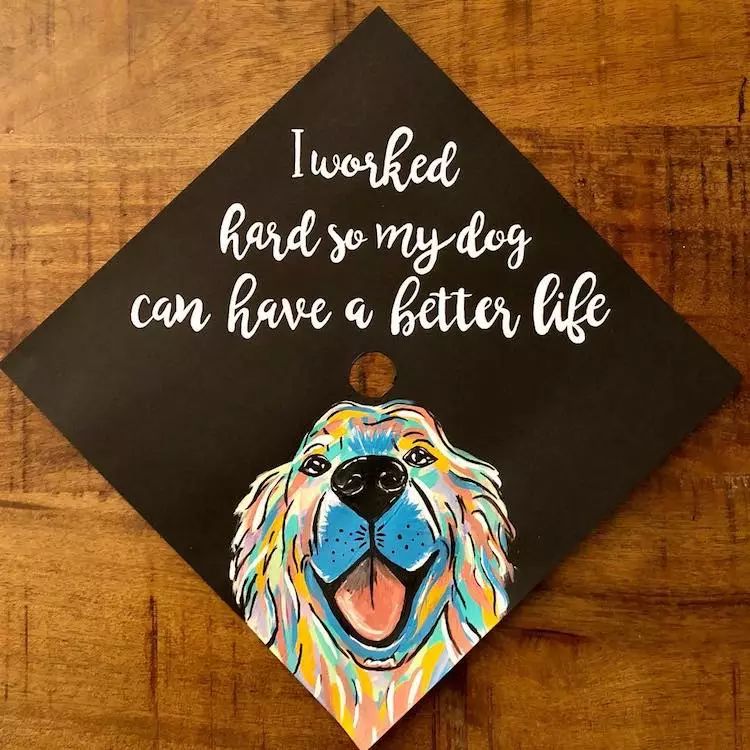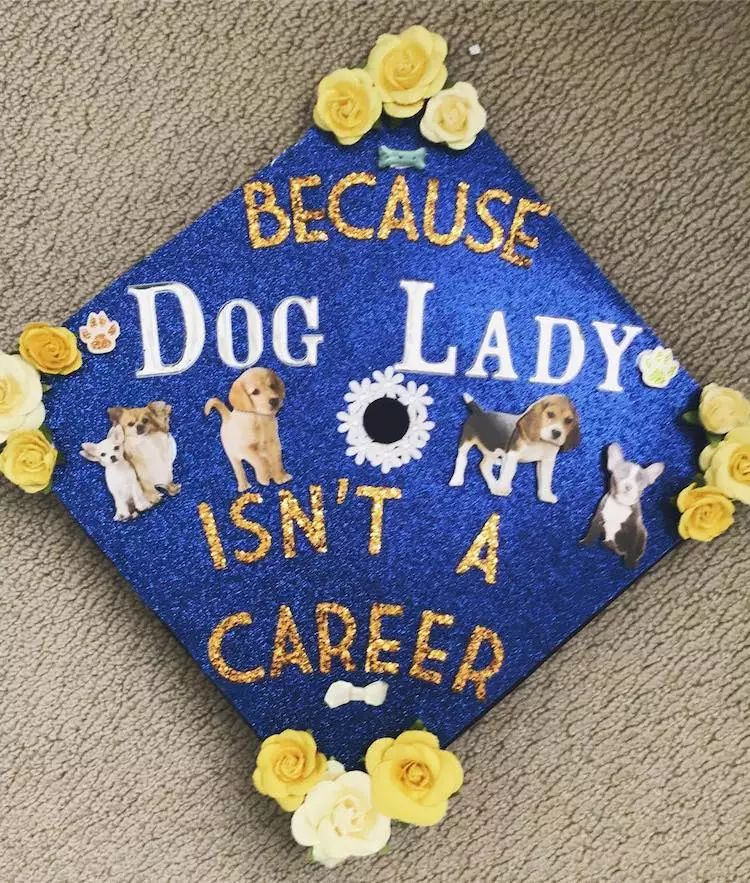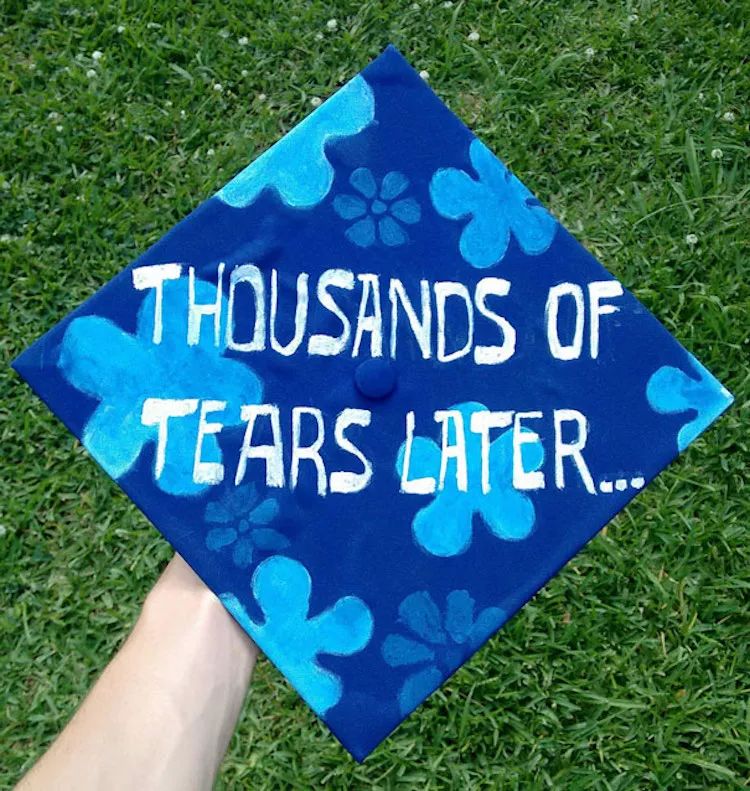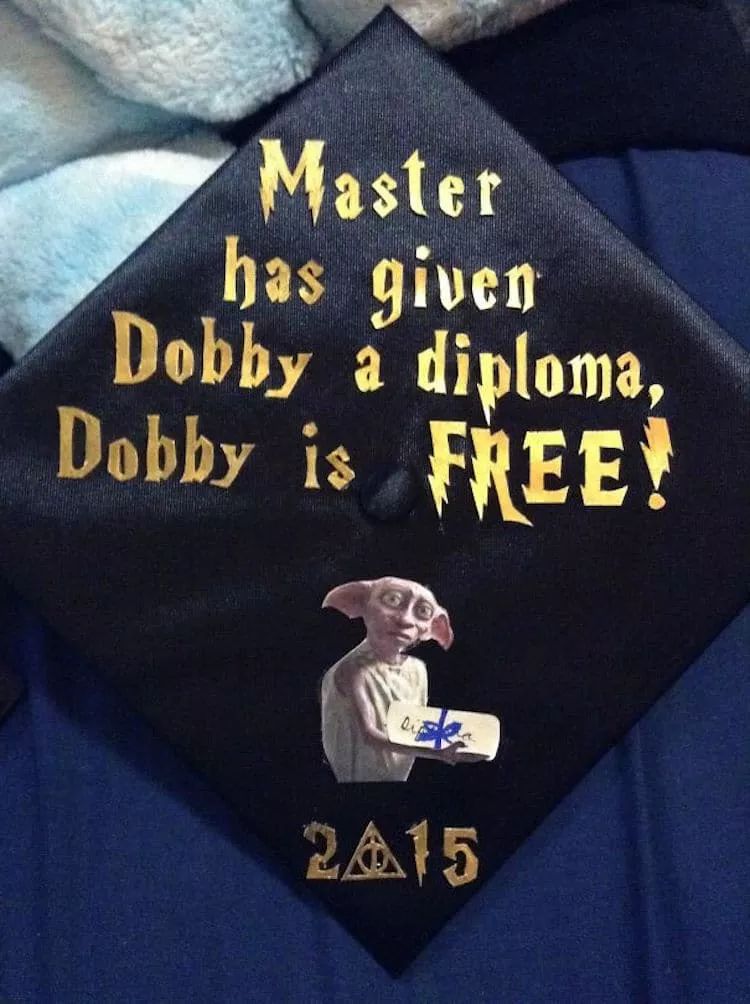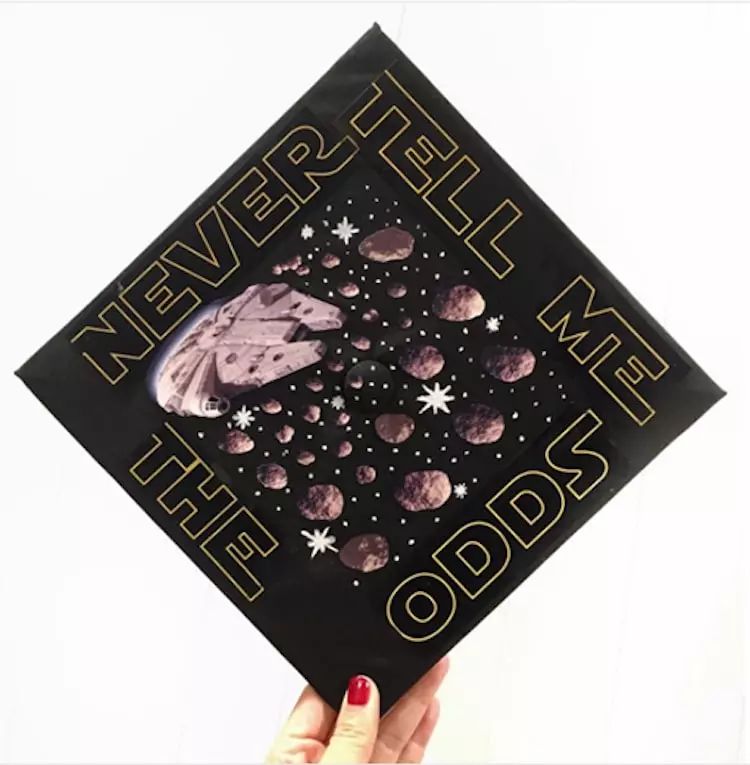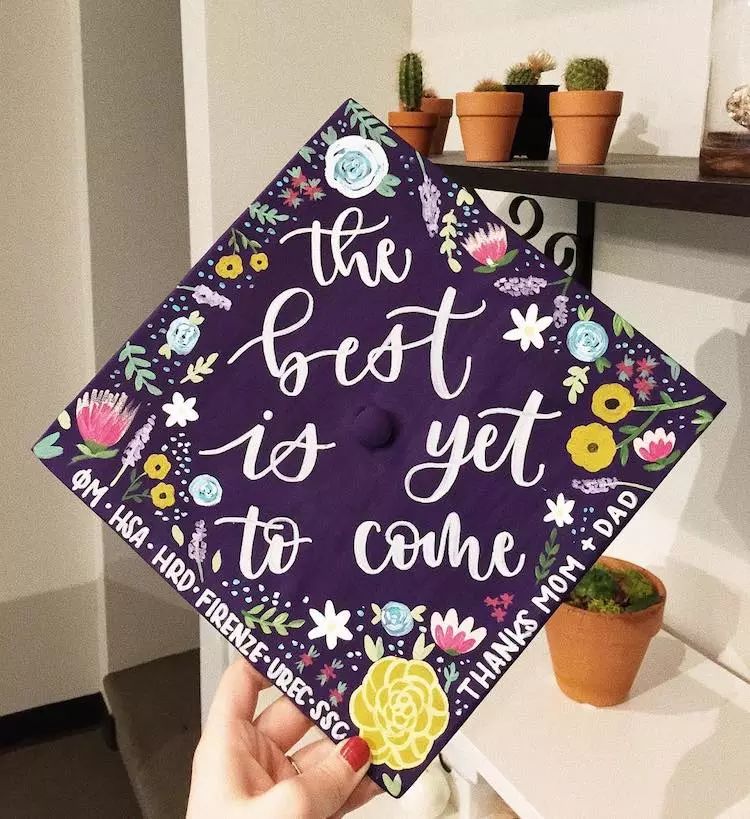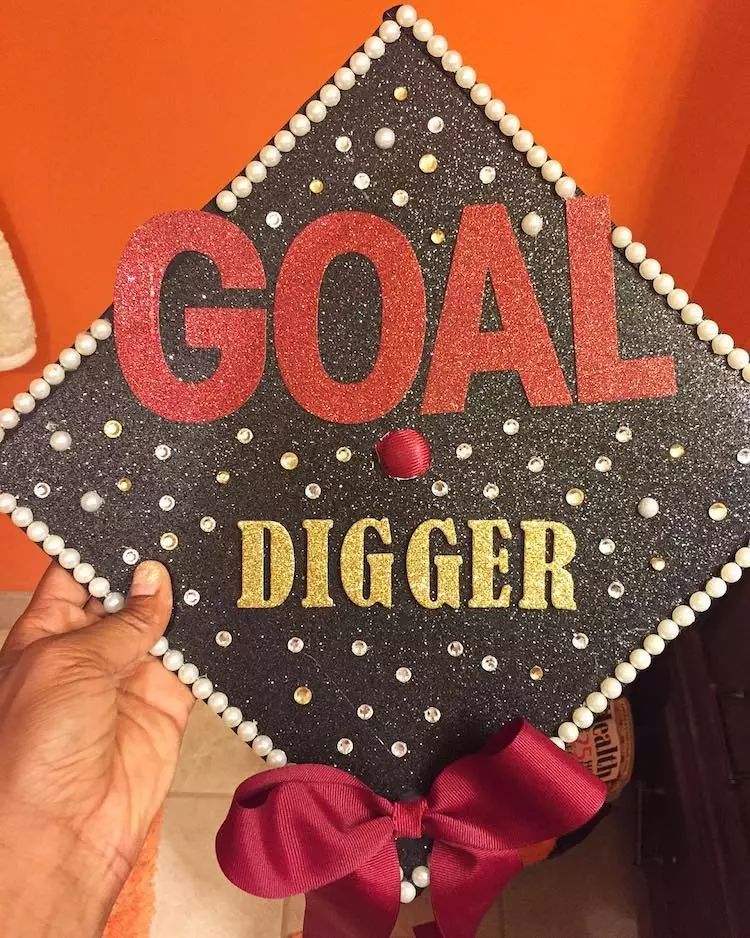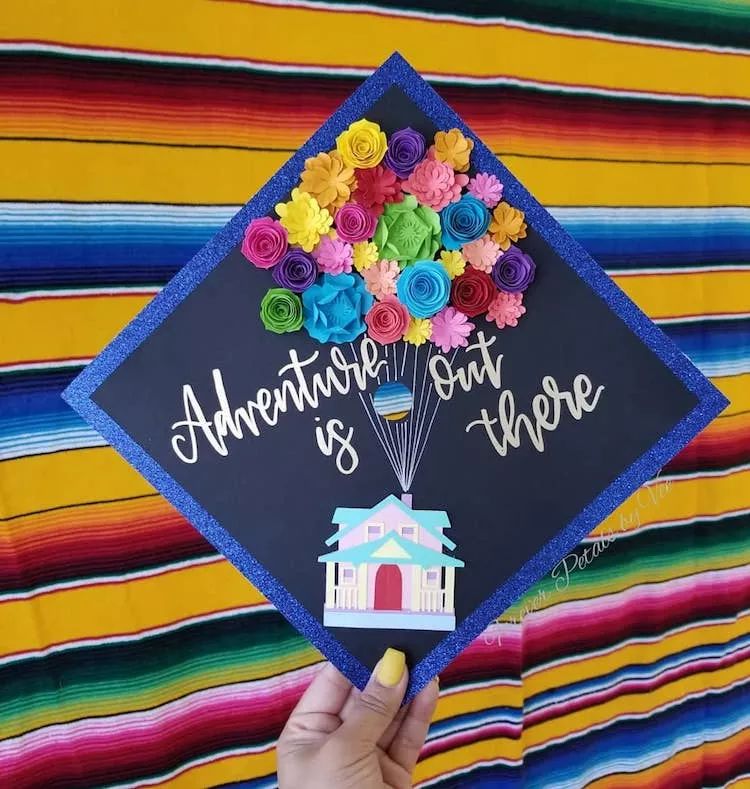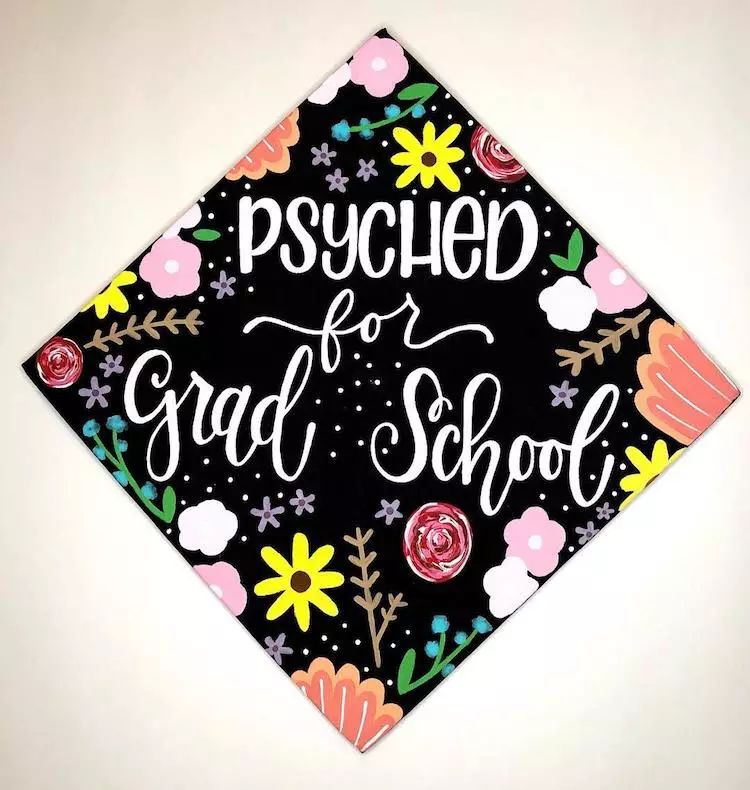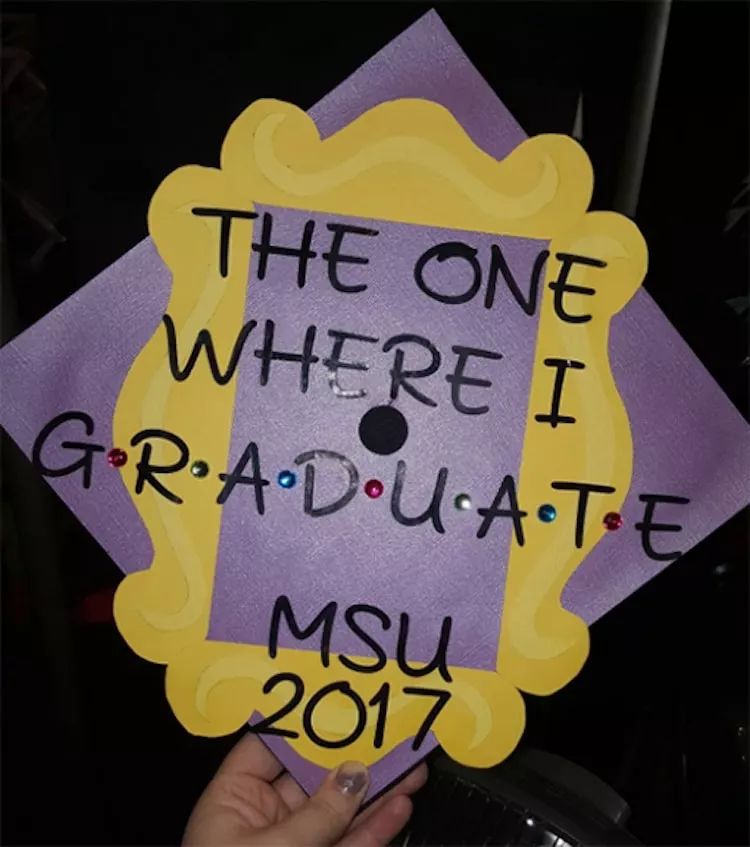
34款画风清奇的学士帽,看完我爱上了字体
转眼之间,已经是五月末了,每个学校的学长学姐们又要面临毕业了,又是一个平淡却又激情,朴素却又浪漫的毕业时节了。
就我个人而言,似乎每一次毕业都是那么的平淡,甚至没有什么让人感动的回忆——也不知道是我天性凉薄,还是校园生活太过乏味。
但真要说,其实「毕业」还是相当值得纪念的一件事,也是一个非常好的总结人生的节点。而最适合用来作为记录的载体之一,就是戴在你头上的学士帽。
我特意搜集了34个国外学生曾经「设计」的学士帽,并将他们分类展示给大家。也许他们的感叹和吐槽,能给你的毕业经历增添些灵感和趣味。
1.终于解脱的吐槽
虽然说校园里有着青春的各种美妙回忆,但是每个人总是会有些想要吐槽的事情,那么写在帽子上给所有人看就是一个很好的选择——让全世界人都知道你有多努力!
比如说这位emsgemscreations就表示:要不是为了我家狗子,我哪能成功毕业呢?!!!
当然也有比较感伤的,breckenh满是失望的表示:照顾自家狗狗确实不能写进简历里……
除了这些铲屎官,也有真正对于校园生活的吐槽。比如这位island-photo明显就是熬了夜的,估计通宵好久了吧。
也有对于一些社会问题的反应,eyeroll-qween也许就是熟练地运用了反讽的手法:没错,老娘就是来抢你们工作的移民,来打我啊!
而lizziehjelle的话,更像是一个宣言:然而,她坚持了下来!这孩子一定非常的努力吧!
2.满怀诚意的感谢
有吐槽,自然就有感谢。每一段人生,总有一些话要对一些人说。比如我们的家人:
来自erbanqueen
ampupino表达了对于父母的感谢也就算了,那个coffee明显把画风搞跑偏了呀!
事实上,果然有一大票跑偏了的感谢出现了:aww.sam表示,我哪里是什么天才呢?我只不过是把别人喝咖啡的时间,用来吃甜甜圈了!
从vivi2425的毕业帽子上能看出,这孩子一定没少去蹭星巴克的wifi和空调。
whatisgoingonrightnow表示,咖啡有毛用?!披萨才是真正的力量之源!
3.玩梗大神的作品
当然对于Nerd来说,怎么能少了最喜欢的影视作品呢。这么好的玩梗机会根本不能放过啊!
虽然权游已经烂尾了,但是助学贷款不会轻易结束(你看这位King-noro同学笑得多开心啊!)
海绵宝宝本来多么欢乐的画风,但是为什么这位Backs-People-Up同学的话让我感觉这么伤感……果然做毕设的泪都来自当年选专业时脑子里进的水啊。
biblioceratops一看就是资深的哈迷,连字体都完美复刻了,不过我倒是第一次看到把自己带入非人类角色的……
华纳的《哈利·波特》都出现了,迪士尼的粉丝怎能停滞不前?melissalovesdisney从ID上就宣布了自己迪士尼粉丝的身份,并且同样复刻了经典的星战字体——抱歉,迪士尼有IP就是可以为所欲为。
来自密歇根州立大学的itsrachelnoel则将《冰雪奇缘》画在了自己的帽子上——毕竟是曾经的爆款。
不过同样来自密歇根州立大学的abbistec的帽子就有点平平无奇,也有可能是ta的梗我没看懂吧。
lvoekat则使用了《狮子王》之中最经典的祈祷词:Hakuna Matata——意为「无忧无虑,梦想成真」。
foreverpetalsbyvee则用《飞屋环游记》的梗来激励自己。
4.走向未来的动力
鼓励自己也不一定要用玩梗的方式,只是一两句话也足以鼓舞人心。
来自abeauty-and-abeast
drea.oz则道出了「梦想家」的最快乐的事情:你可以说我在做白日梦,但在这条路上我并不孤独。
来纽约找我吧!那是我战斗的地方!——knsiemering
uncappedcreations对于未来的热切期望,洋溢在文字与图画之间。
我是这么理解allisonslettering的这句话的:你终将成为你希望成为的那个样子!
bee-creative-event-planning的这句话相当的霸气,想来他一定完成了不少他曾经设定的目标吧。
adeline-letters表示:这才不是终点!最好的一切尚未到来呢!
5.平平无奇与意义不明
也有一些我觉得有些一般的,或是看不太懂的设计……毕竟我还是才疏学浅,眼皮子浅,如果说错了各位要担待啊。如果有大手子,请一定说出自己的看法吧!
popwithlo的帽子其实不错,可惜就是在那么多有个性的帽子里,这个极简风的帽子确实有点平庸了。
artworkbybria同学,我真的不太明白如果是「Did」,这句话我该如何理解。
vivsrivs同学,你是想说这是你第一次成功毕业吗?
LaVozdeAztlan同学,我能基本看明白你似乎是在开玩笑……但是我必须承认有时候我真的看不懂花体字啊——虽说这不一定是花体字。
destinypashani这应该是一位学校中的风云人物……能明示自己「QUEEN」的称号的绝非一般人。
当我们赶到现场时,victoria-salerno只留下了这样意义不明的话语。
呃,briannedanielle可能是想说,知识让人更性感?
randpajoescandycompany同学,所以说你到底推荐大家去哪里啊?
无论吐槽也好,感谢也罢;平庸也好,浪漫也罢,「毕业」终归是人生中相当重要的,值得纪念的一个节点。
如果有可能,尽量还是留下点痕迹,免得后来后悔自己啥也没干。
比如说我就比较后悔,因为当年的学士服是统一租来的,没法做太多改动。